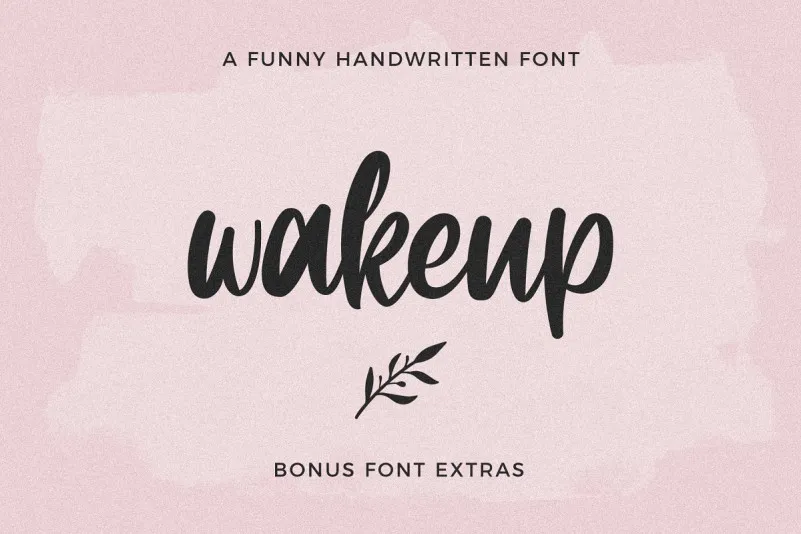
Wakeup Script Font – Download Grátis
Aqui está uma versão em português para a descrição do download da font ‘Wakeup Script Font’, mantendo os requisitos fornecidos: A fonte ‘Wakeup’ é um belo script inspirado nos trabalhos de letra à mão. Esta fonte trará seu design mais elegante e artístico, dando vida ao estilo único desta fonte de script grosso. Disponível para uso em diversas aplicações, como casamentos, convites, títulos de livros, design de rótulos e muito mais, ela é perfeitamente indicada para negócios próximos às mulheres. Desenvolvida pela 24Design Studios, esta fonte tem uma forte personalidade feminina. Com propriedades engraçadas e delicadas, ‘Wakeup’ está disponível em formato de download. Afonte traz um toque sofisticado aos seus projetos gráficos, destacando-se entre as opções de script disponíveis no mercado. Para quem busca uma fonte que se destaca por sua estética única e feminina, sem dúvida, a ‘Wakeup Script Font’ será uma escolha perfeita. Suas funções multifuncionais permitem que você crie designs com muita personalidade para um vasto leque de aplicações gráficas.